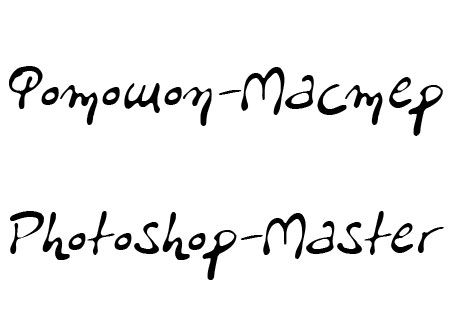
очень хороший шрифт.Но использую редко.Не всегда понятно что написано
гениален) чётко в мой коллаж вписывается)
Здорово использовать в работах, имитирующих рисование акварельной кистью.